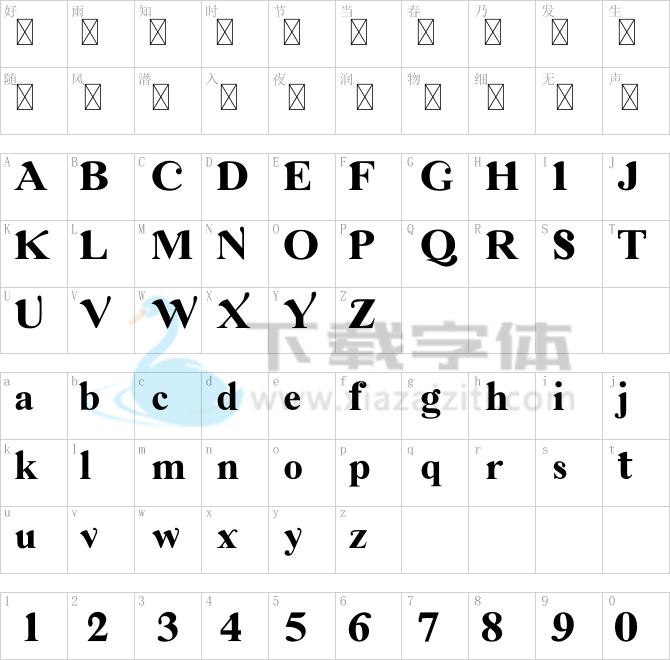
Amboqia Boriango.otf字体下载,这款字体结构工整、笔画清晰,兼顾美观与易读性,适用于标题、正文、海报、包装、LOGO 等多种场景。字形优雅稳定,风格百搭耐看,适配日常排版与创意设计,让文字呈现更舒适、更具质感。Amboqia Boriango.otf字体下载一笔一画,皆是细节,以均衡的比例、流畅的线条打造舒适视觉体验,字形端正大气,风格简约现代。无论是商业设计、品牌宣传还是日常排版,都能轻松驾驭,让文字更有格调与力量。Amboqia Boriango.otf字体下载字体下载。